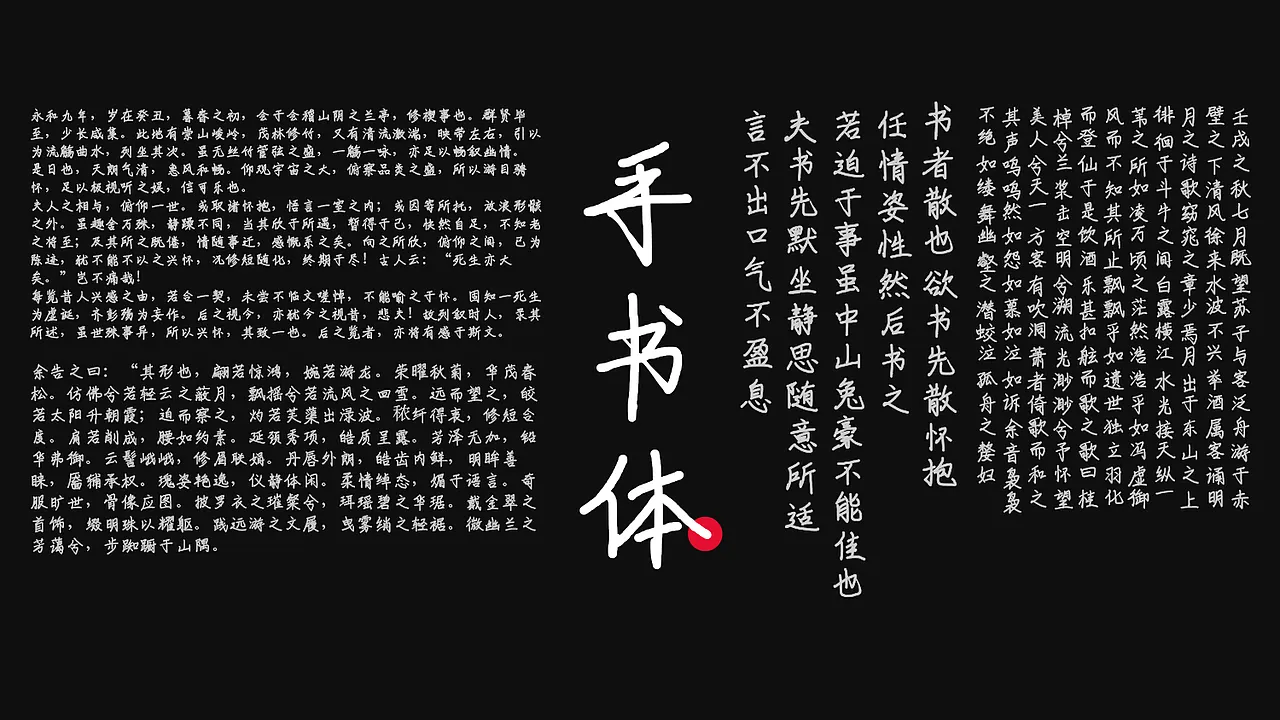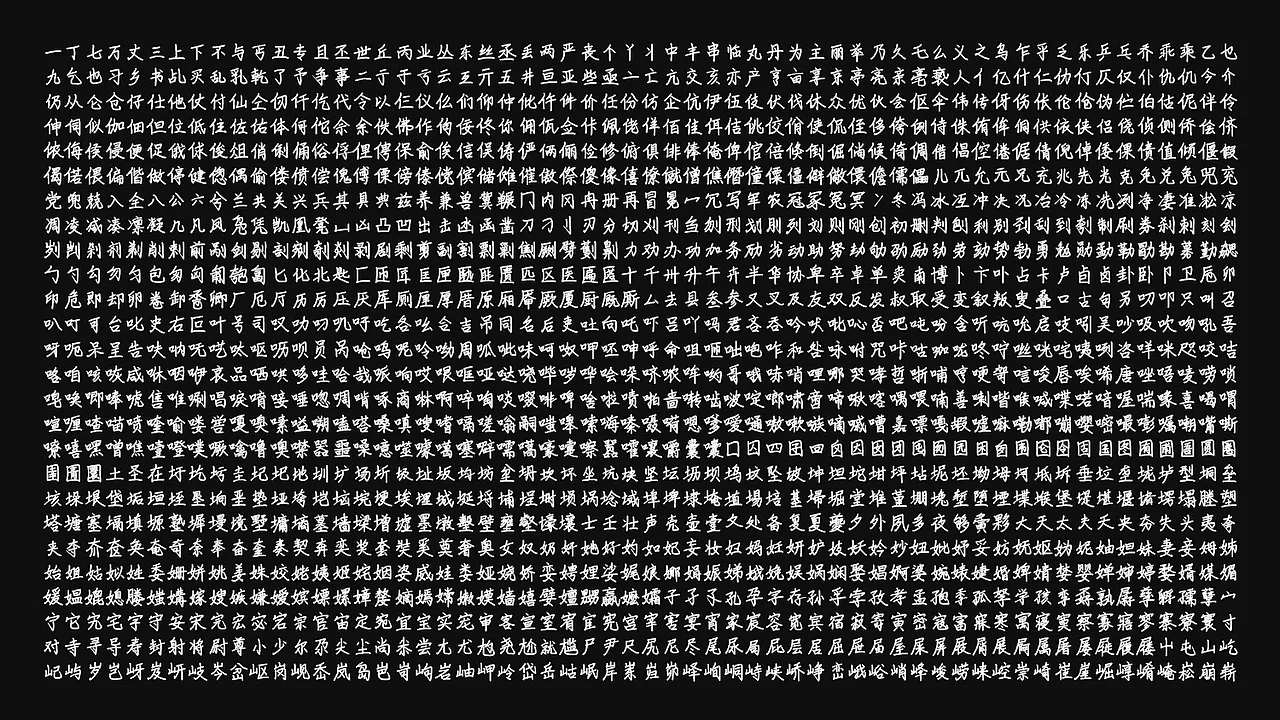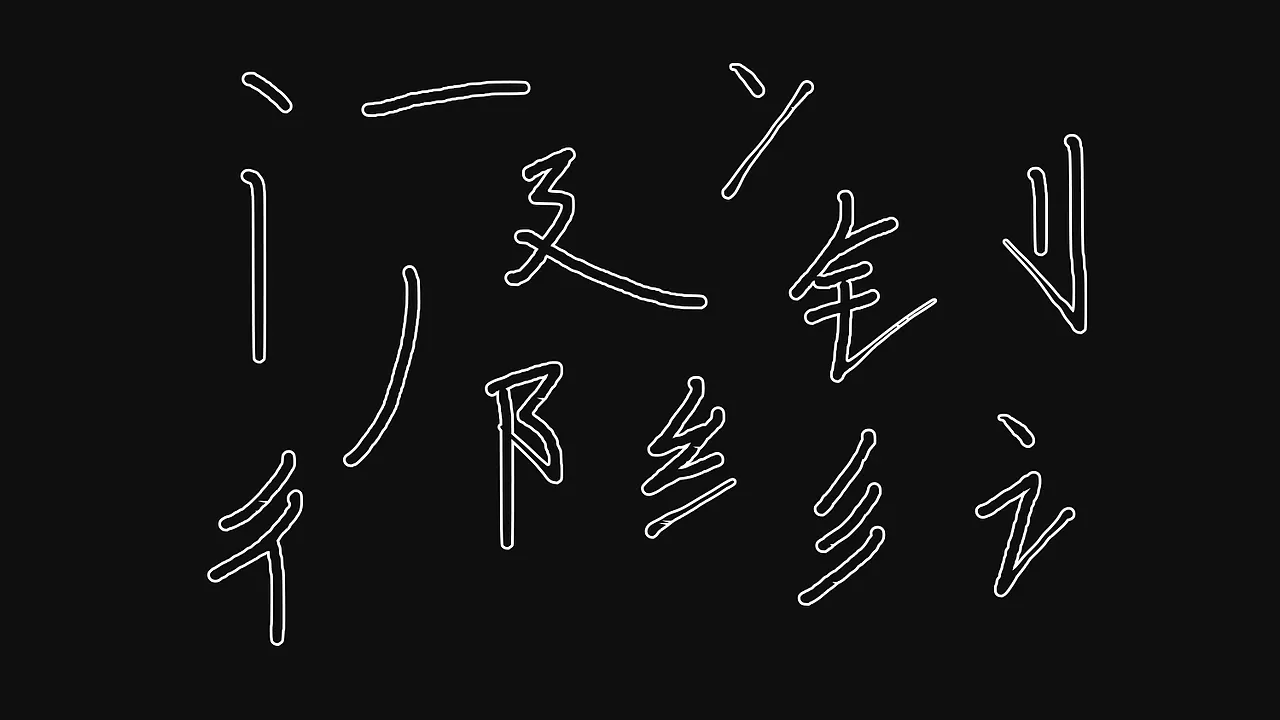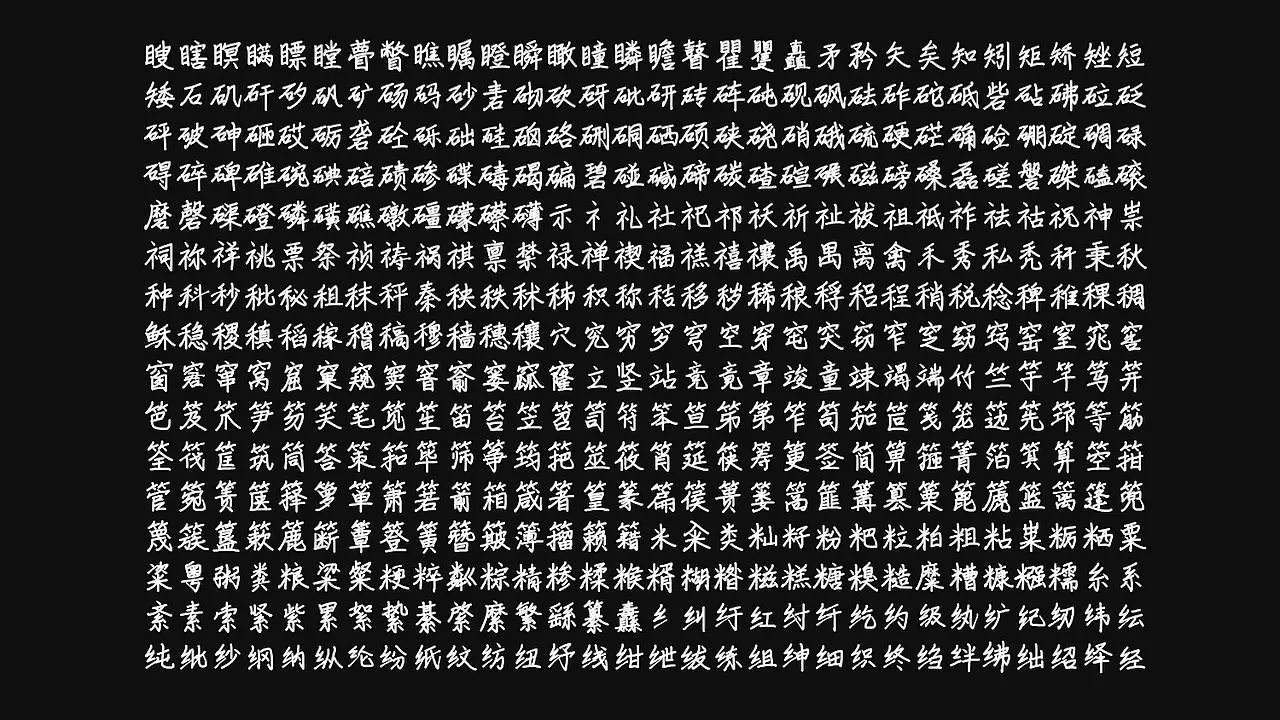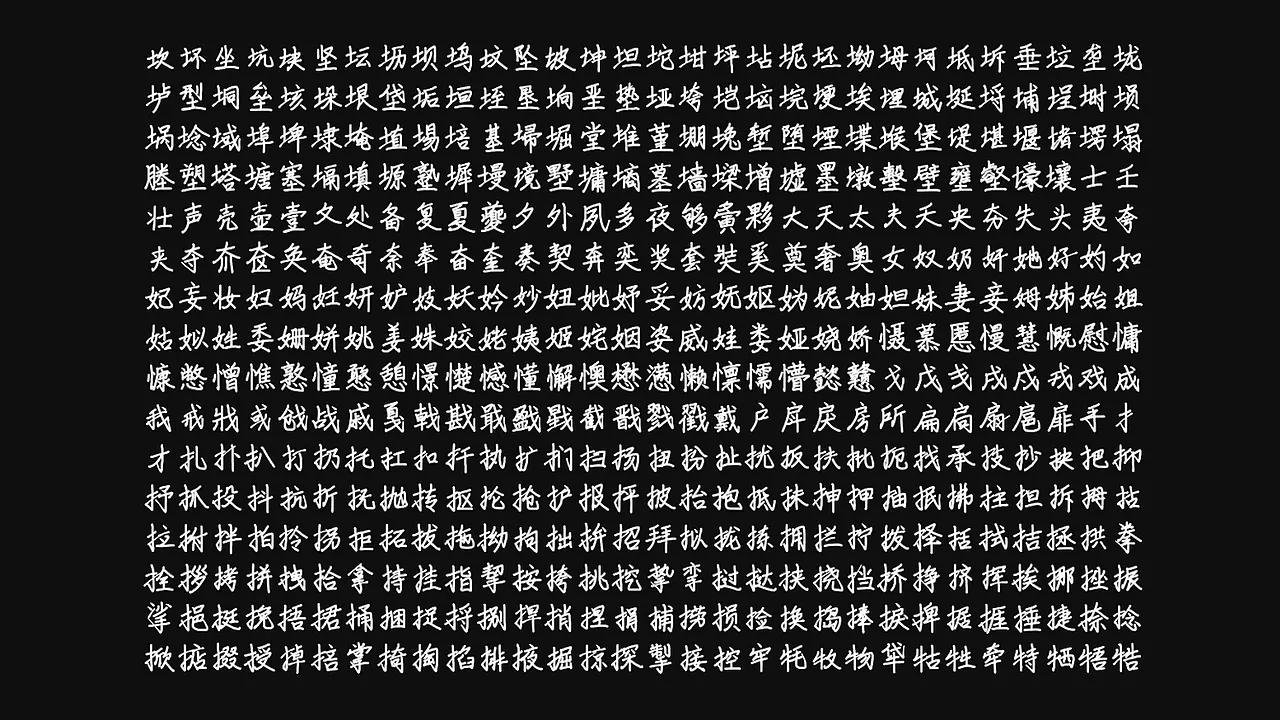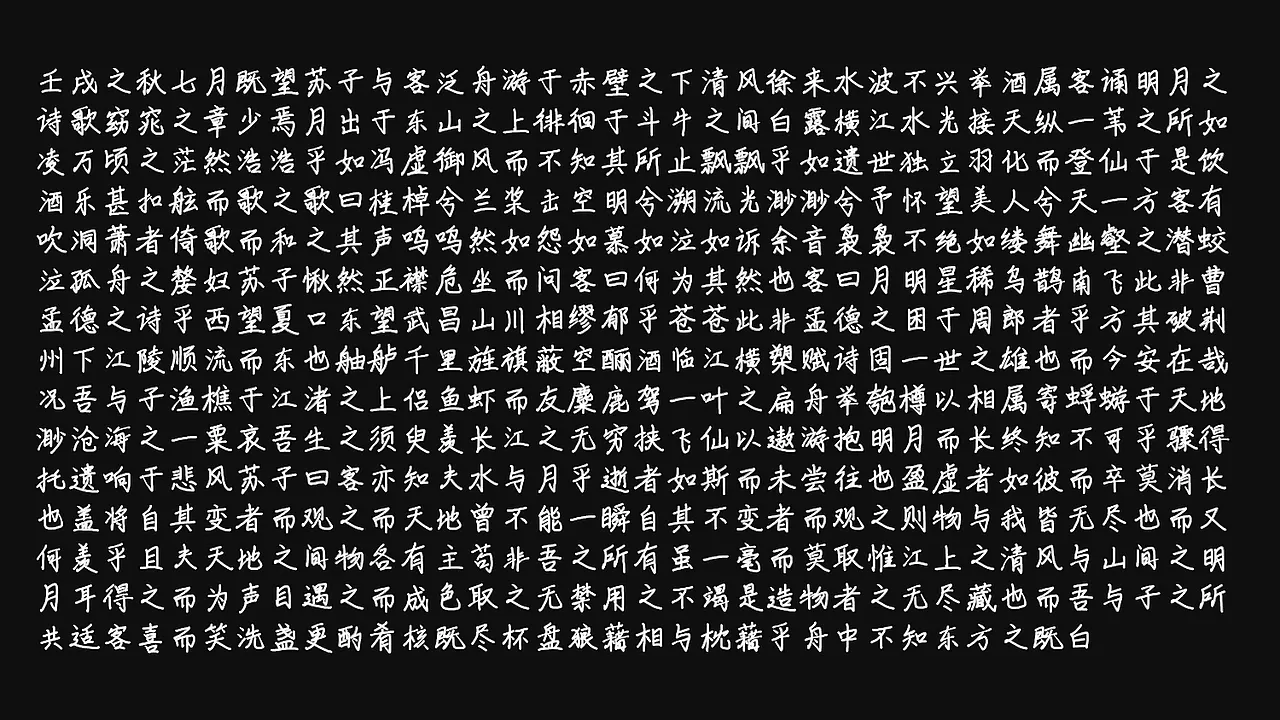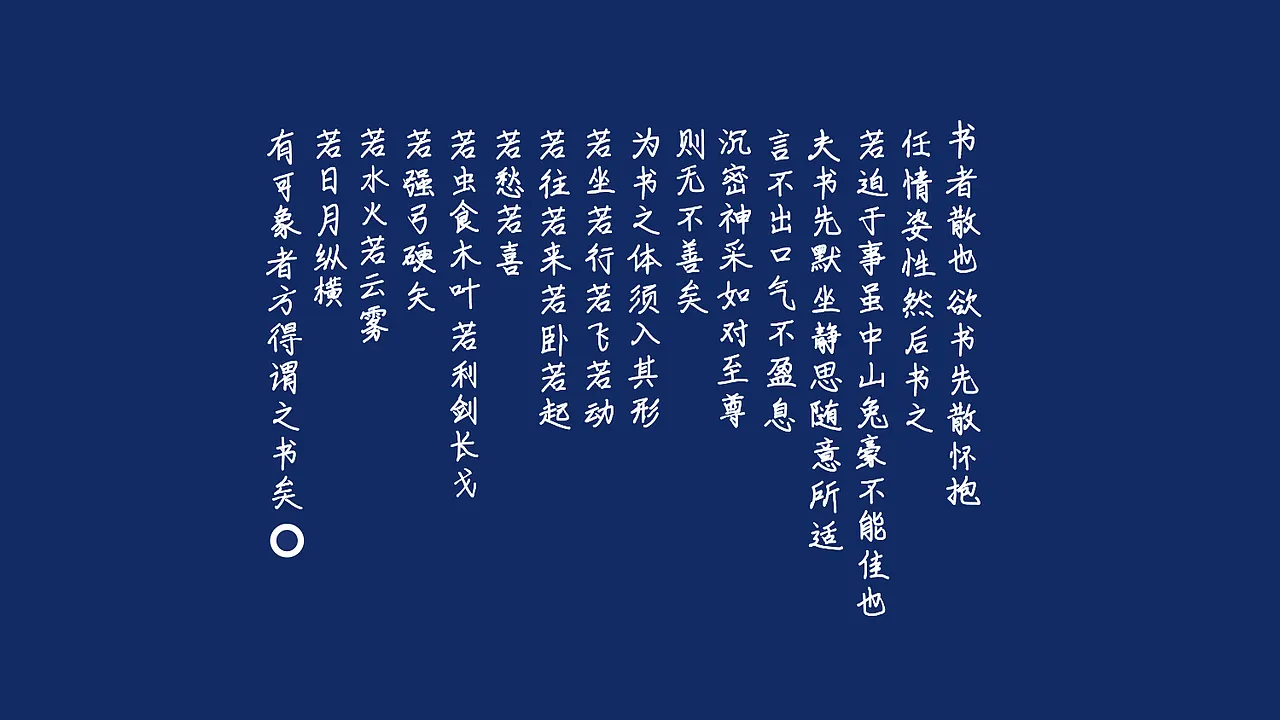
花了挺长一段时间反复调整和校对,这版中文手书体总算能正式拿出来跟大家见面了。为了让大家拿到字的时候不觉得割裂,我一遍遍调不同字号下的显示效果,连结构相近的偏旁部首都单独拉出来对过笔形,中间还推翻了好几次重心布局,好在现在这套版本算是彻底理顺了。这次一共把最常用的基本汉字做了6763个,日常图文处理里绝大部分场景都能直接够用。字体文件直接放在这里,点开就能下载,大家拿去自己商用完全不需要额外去跑授权流程,不管是印在T恤上、放进电商详情页还是剪进短视频里,直接拖进设计软件就能用,省去一堆沟通成本。整体字形走的是自然的手写路线,没有刻意去卡那些规整的网格线,笔画的起承转合都留着手工写字的那种随意感,收笔会稍微带点自然的停顿,转折处也不做过度打磨,所以视觉上看过去不生硬也不呆板。平时在做 slogan 标语、产品 banner、活动海报或者搭配商标 logo 的时候,都能直接把它嵌进去,它这种略带呼吸感的字重变化和错落节奏,能让整个排版的视觉流动变得更灵活贴切一些,不再被标准字体的方正框架框住,而是顺着你的画面情绪自然铺展开来。